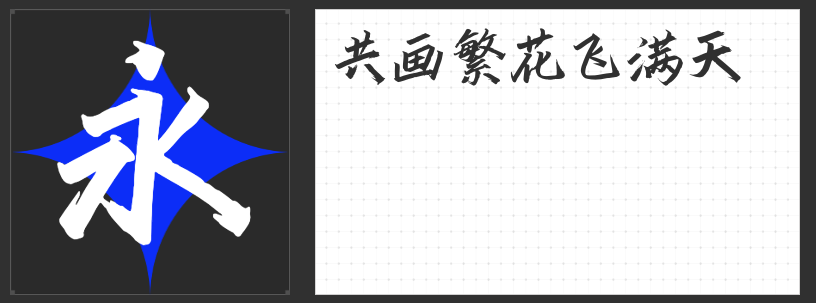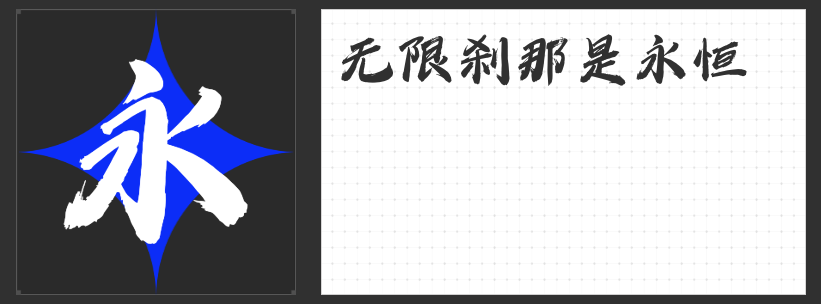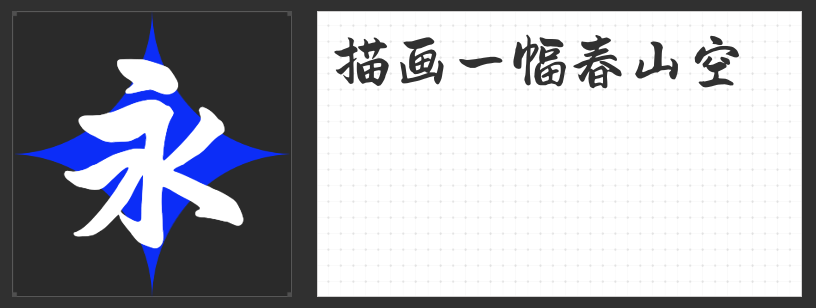
墨韵天成:四款毛笔字体解锁东方美学新境界
毛笔字体以水墨为骨、气韵为魂,在设计中承载着东方美学的独特表达。以下四款风格各异的毛笔字体,以笔触为语言,在传统与现代之间架起桥梁,为设计注入浑然天成的艺术张力。
一、造字侠今朝醉简
这款毛笔楷书以“醉”为魂,笔锋如刀锋出鞘,收笔处凌厉的飞白似酒意未散时的挥毫,既有正统楷书的法度森严,又暗藏狂草的洒脱不羁。笔画转折间暗藏劲力,如金石相击,在克制中迸发张力。其雄浑的笔触尤其适合传递力量感与历史厚重感,为设计注入豪迈的江湖气魄。
二、高手兵克逍遥体
字形取法古碑帖的端庄骨架,却以现代设计思维重构笔画细节。收笔处如利剑归鞘的锐利顿挫,赋予字体动态的平衡感;横竖撇捺间保留毛笔的天然肌理,却通过简化结构提升视觉识别度。这种“破而后立”的设计哲学,让传统毛笔字在保持文化底蕴的同时,焕发出符合当代审美的先锋气质。
三、造字侠陈坤风行简繁
以行书为基底,笔画如风过竹林般轻盈流转。字中偶现的点睛之笔——或是一捺的舒展,或是一竖的悬针——恰似水墨画中的留白,赋予字体呼吸感。圆融的用笔与洒脱的结构相得益彰,既保留手写温度,又通过精密的笔画控制实现现代设计的秩序感,适合传递优雅与灵动的双重气质。
四、万人字造踏歌行体
方整严谨的结体暗合篆隶的庄重,斑驳的笔触却诉说着岁月侵蚀的痕迹。用笔方圆兼备,起笔如刀刻,收笔似墨晕,在刚柔并济中构建出蓄势待发的动态平衡。这种对古法的忠实再现与现代审美需求的微妙平衡,让字体既可作为文化符号承载历史记忆,又能以独特的视觉语言融入当代设计语境。
这四款字体以毛笔为媒介,在宣纸上书写设计的新可能。无论是追求酣畅淋漓的笔墨意趣,还是探索传统元素的现代转化,它们都能以独特的姿态,为设计注入超越时空的美学力量。